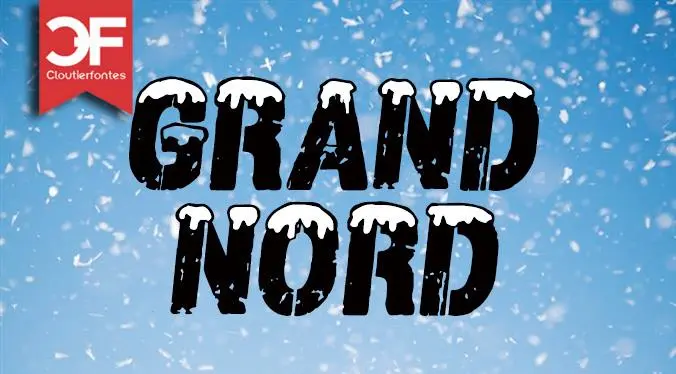
CF Grand Nord font – Download Grátis
A CF Grand Nord é uma linda fonte de display criada pelo designer Hamilton, perfeita para criar textos chamativos e distintivos que destaquem seu trabalho na web ou nos ambientes digitais. Ela traz um mix sofisticado entre linhas arquitetônicas e estilos futuristas, garantindo sempre uma presença forte e moderna em qualquer projeto. Para usuários de propósito pessoal (como criação de blogs, sites ou publicações online), a fonte está disponível gratuitamente. No entanto, para quem busca usar a CF Grand Nord no âmbito comercial e deseja utilizar um número maior de caracteres, uma licença adicional é necessária. Esta opção permite que você explore todas as possibilidades criativas da fonte sem limitações. Esta linda fonte está disponível na categoria Display Fonts, trazendo uma experiência visual única capaz de destacar seu trabalho em qualquer plataforma digital. Com sua elegância e modernidade, a CF Grand Nord é uma escolha inteligente para designers que buscam uma fonte versátil e impecável para seus projetos futuros.